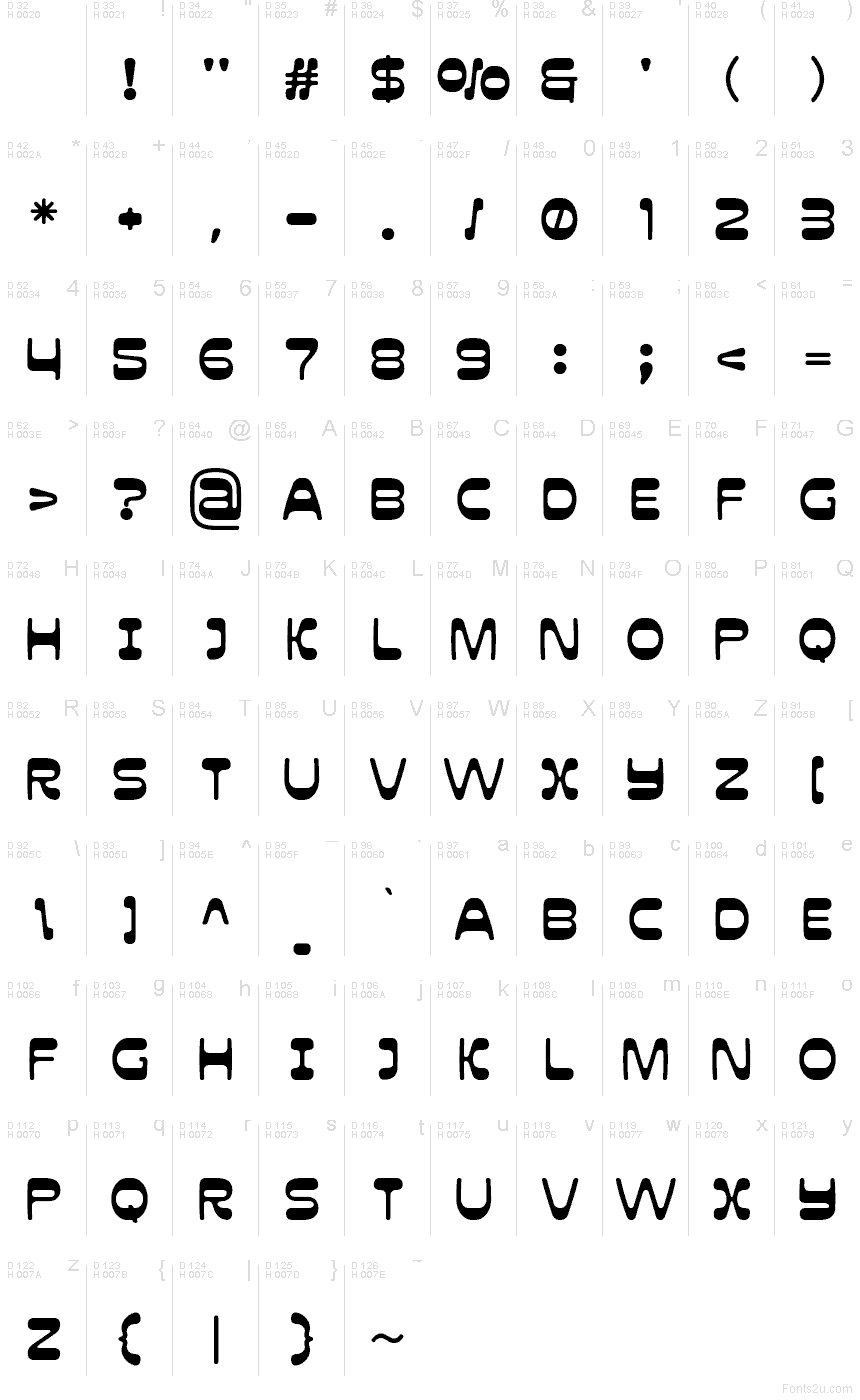
Capestone stworzony przez Linecreative to darmowy, retro krój displayowy z szerokimi, zaokrąglonymi wielkimi literami i sylwetką wyraźnie nawiązującą do lat 70. Miękkie rogi i zwężające się łączenia nadają mu formowany wygląd.
Ta vintagowa geometria pasuje do okładek płyt i plakatów muzycznych, zwłaszcza w klimatach funka, disco czy innych grafik inspirowanych tamtą epoką. Może również kształtować branding marek modowych i swobodnych restauracji, gdzie szerokie formy liter odczytywane są jako spersonalizowany znak słowny. Zaokrąglona konstrukcja nawiązuje do grafiki bąbelkowej i obłych form produktów, dzięki czemu sprawdzi się wszędzie tam, gdzie liternictwo staje się częścią warstwy wizualnej.